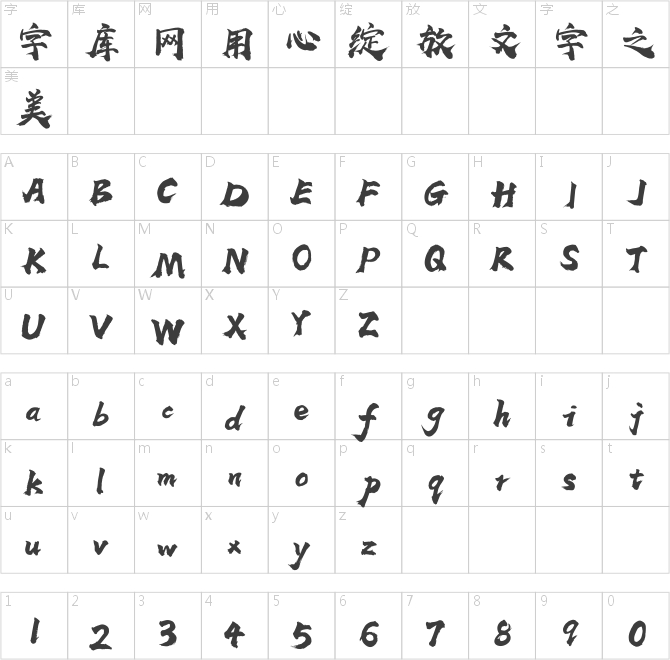
上首華風(fēng)書(shū)法體 詳情頁(yè)
字體名稱(chēng): 上首華風(fēng)書(shū)法體
上首華風(fēng)書(shū)法體
上首華風(fēng)書(shū)法體,字體風(fēng)格穩(wěn)重呈方塊形,字體筆畫(huà)豎折處細(xì)節(jié)處理,是此套字庫(kù)的亮點(diǎn)。字庫(kù)整體特征堅(jiān)硬、有力,具有現(xiàn)代、國(guó)際化的指向性,適用于搭配標(biāo)志、廣告標(biāo)語(yǔ)、商業(yè)廣告等高端屬性。